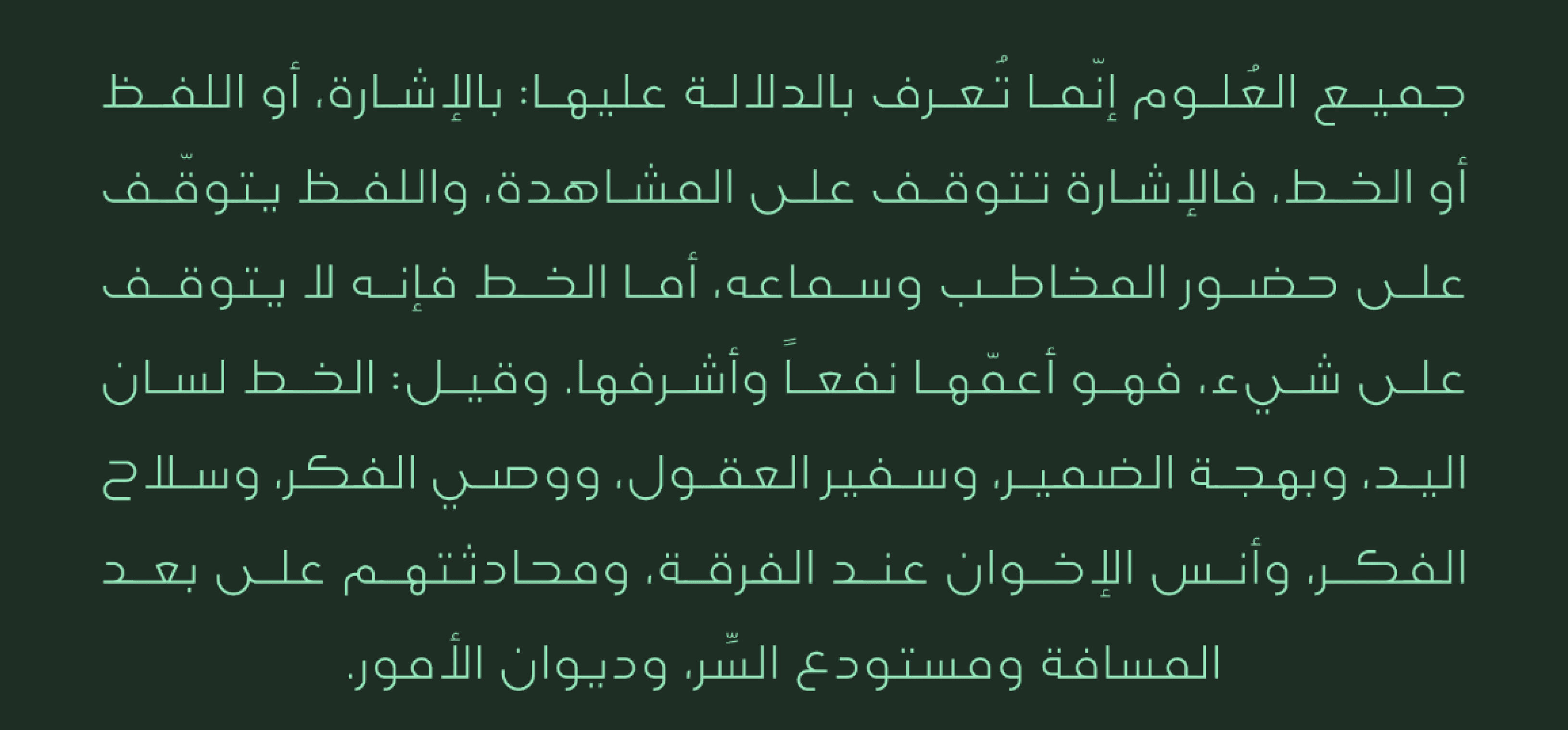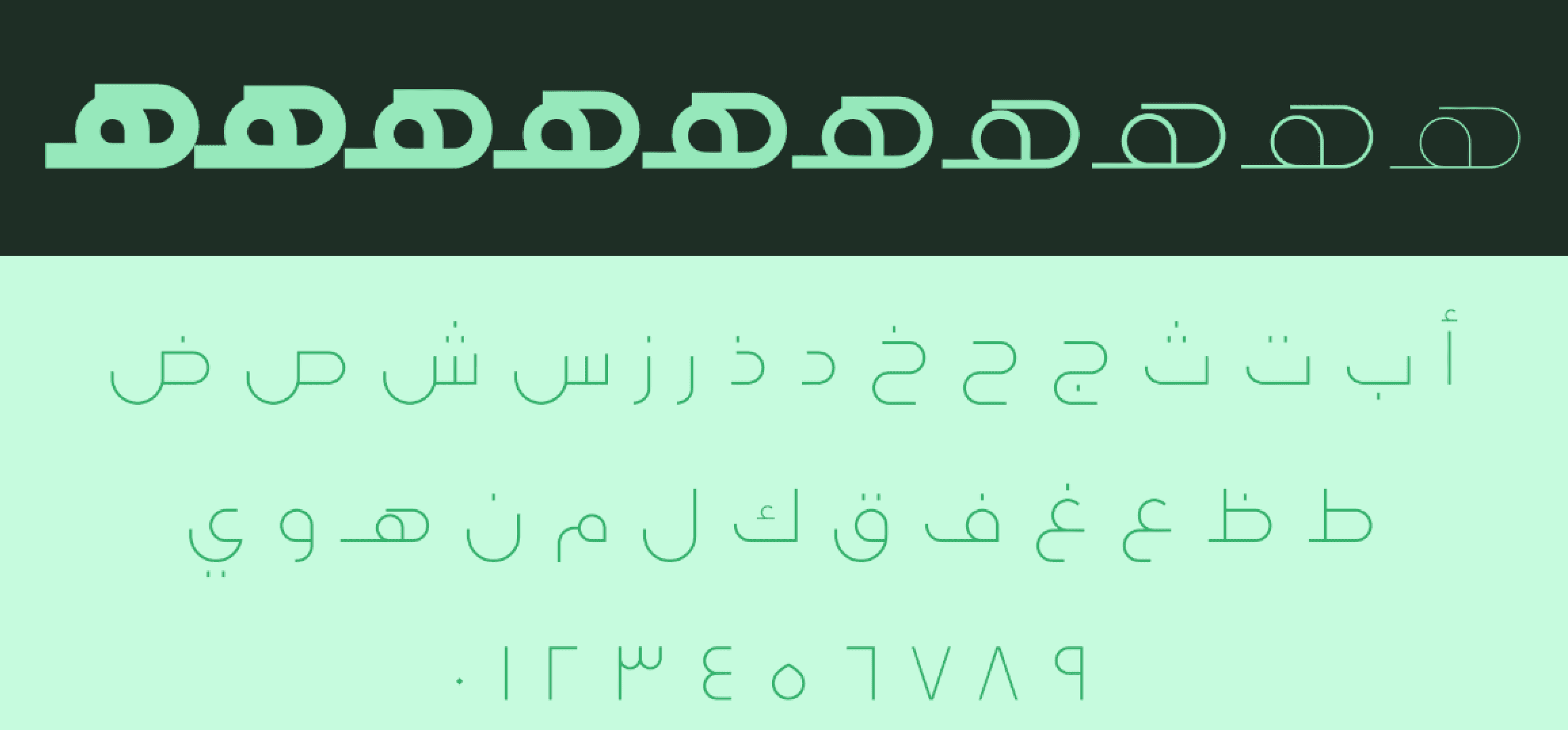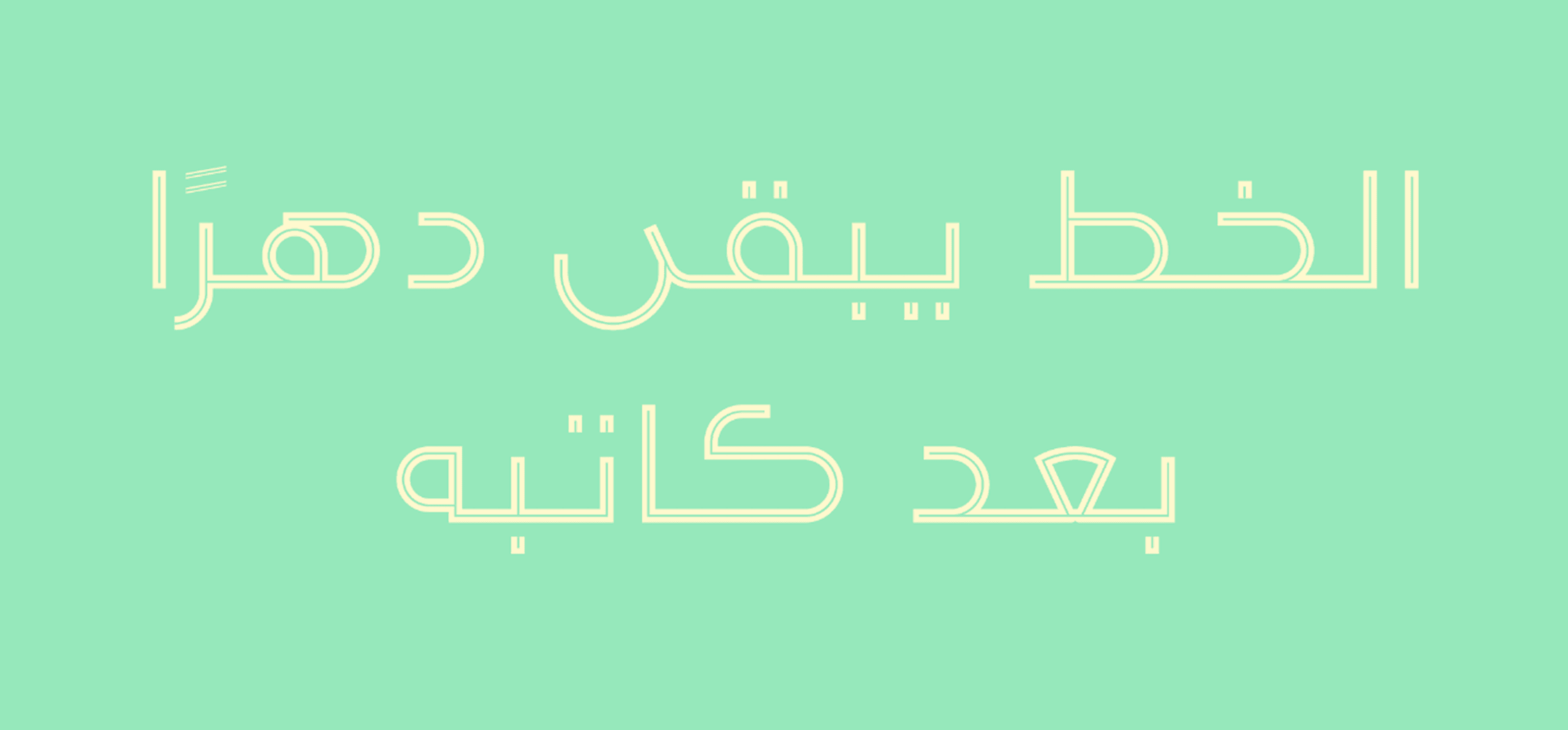
هو خط عربي هندسي عصري بتصميم واضح ومنظم، يوفّر مجموعة واسعة من الأوزان لتناسب الاستخدامات المتنوعة، من العناوين البارزة إلى النصوص الطويلة. يتميز بمظهر متوازن بين البساطة والوضوح، مما يجعله مناسبًا للمشاريع الطباعية الحديثة، مثل العلامات التجارية، المواقع الإلكترونية، والتطبيقات.